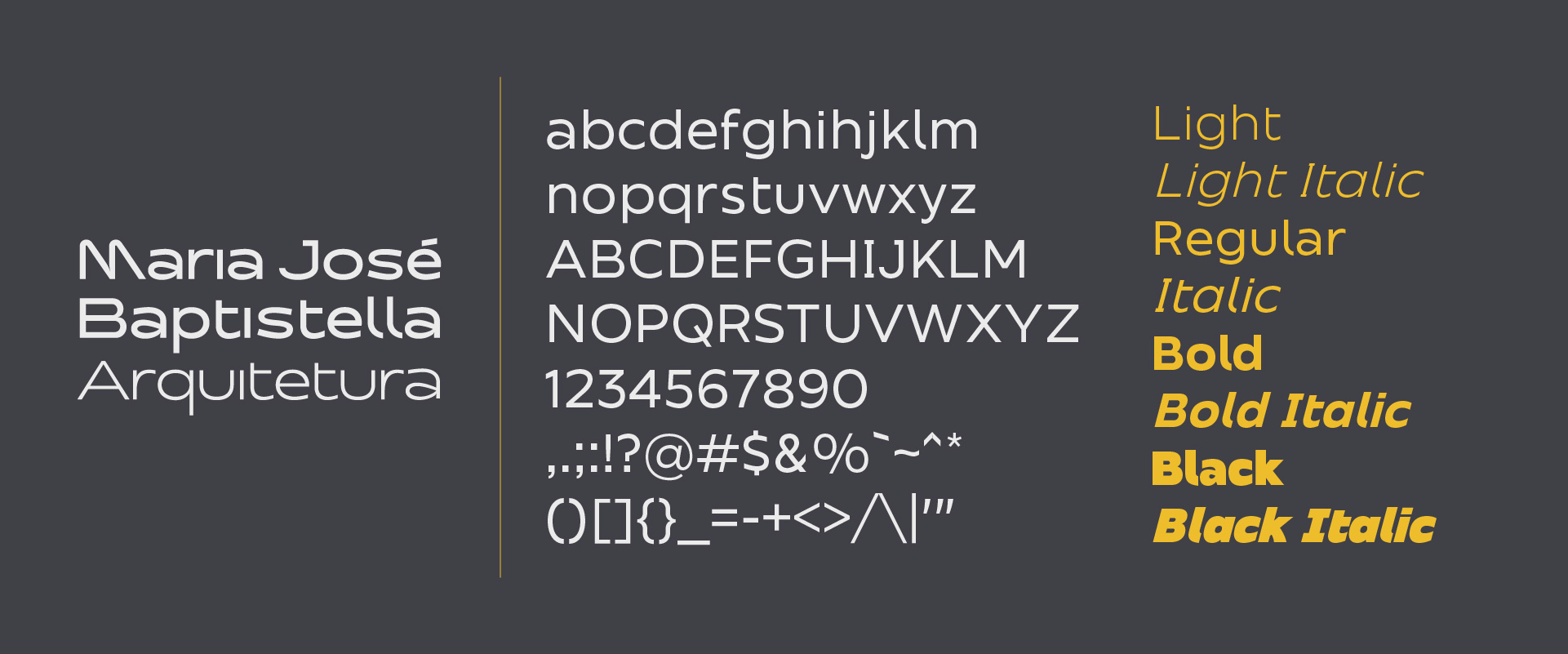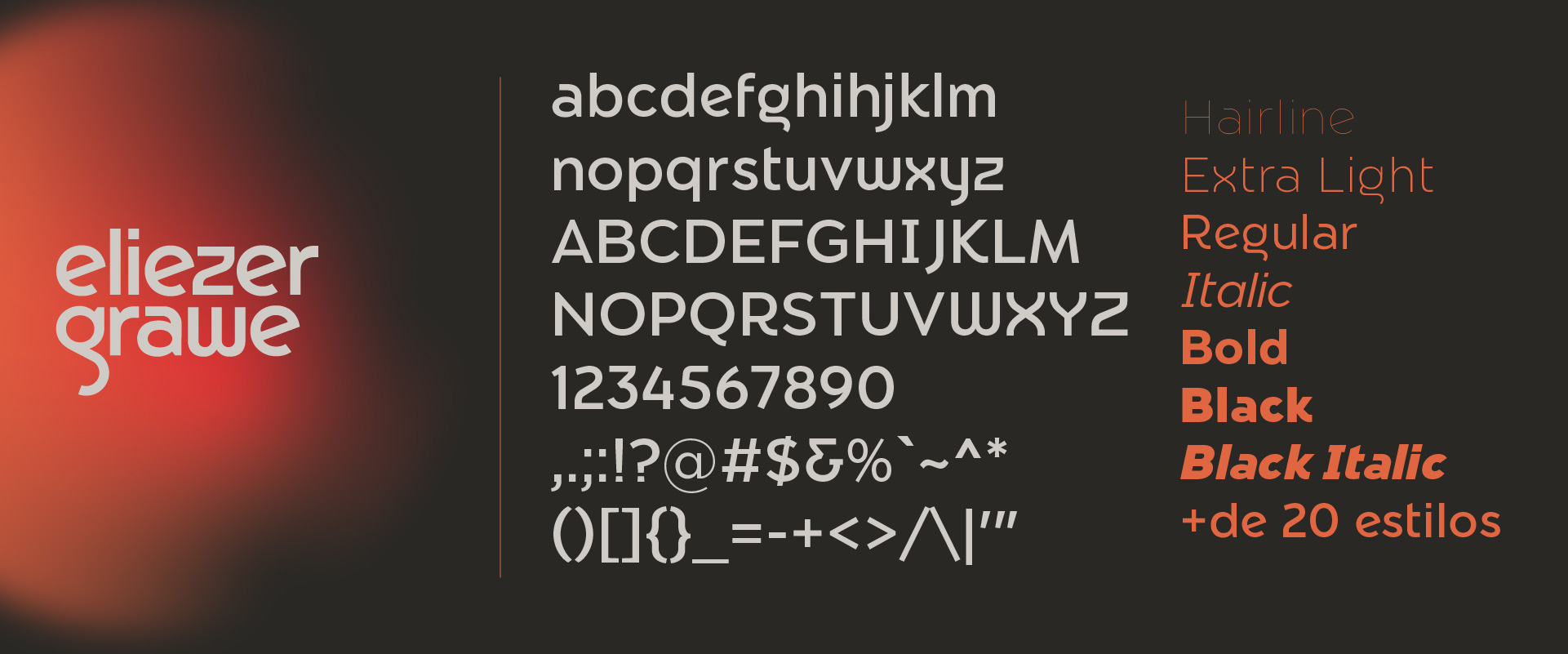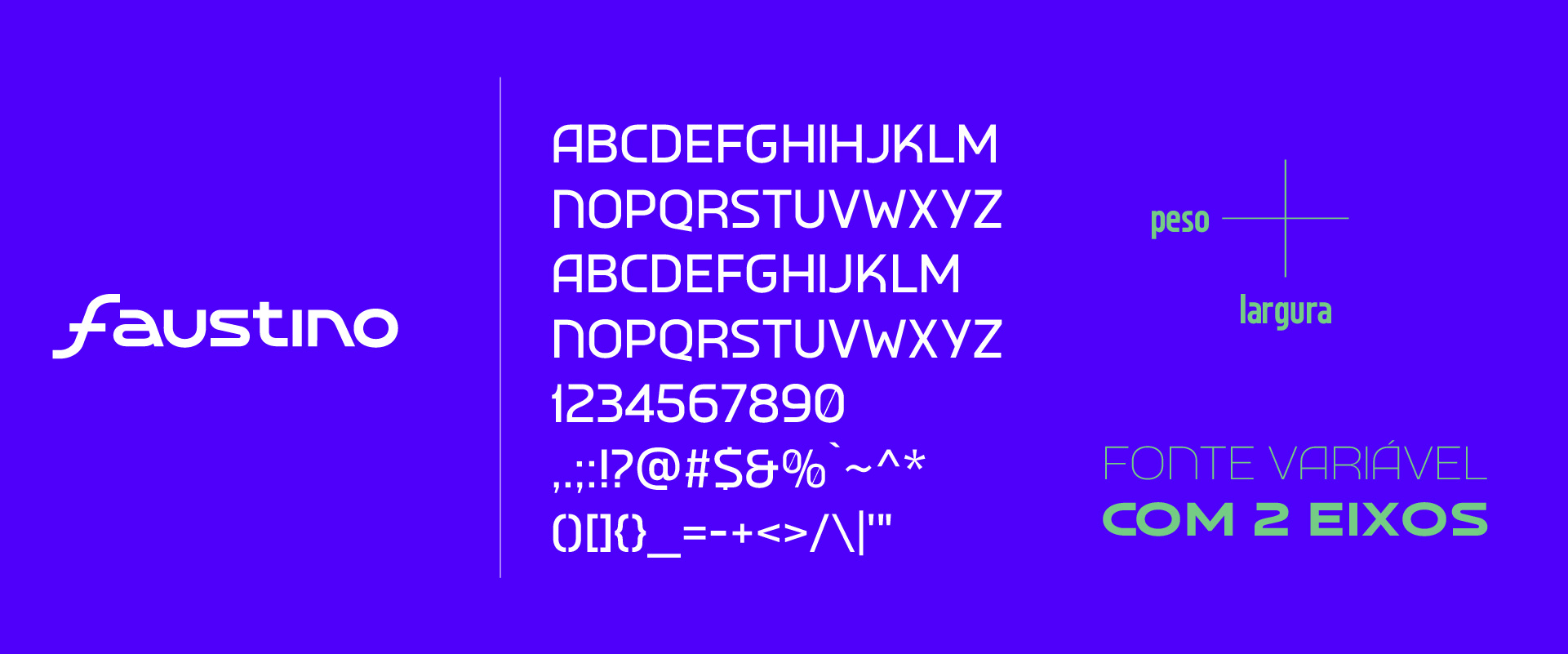
Tipografia única para identidade, comunicação e reconhecimento.
Quando uma tipografia é desenhada especificamente para uma marca, ela deixa de ser um recurso genérico e passa a operar como parte do sistema
Sustenta identidade e traz coerência em todos os pontos de contato, sem remendos por falta de acento ou peso que não existe.
Nos últimos anos pude desenvolver, além da fonte própria Eligra, alguns projetos de fontes sob medida. Confira aqui alguns deles.
Desenvolvida para minha própria marca pesssoal, a fonte Eligra ganhou Bronze no Prêmio Brasileiro de Design Gráfico de 2024. Com vários pesos e estilos, ela é a base da identidade visual de todos os materiais pessoais que crio.
Desenvolvida para a identidade do escritório de arquitetura MJB, a Baptistella é uma tipografia sóbria e direta, desenhada para integrar-se com precisão ao logotipo e ao sistema de identidade da marca.
Cleberson Faustino é um designer e palestrante cuja marca pede modernidade e ousadia. A tipografia desenvolvida para ele traduz esses atributos por meio de um sistema variável de dois eixos, resultando em um conjunto altamente versátil.